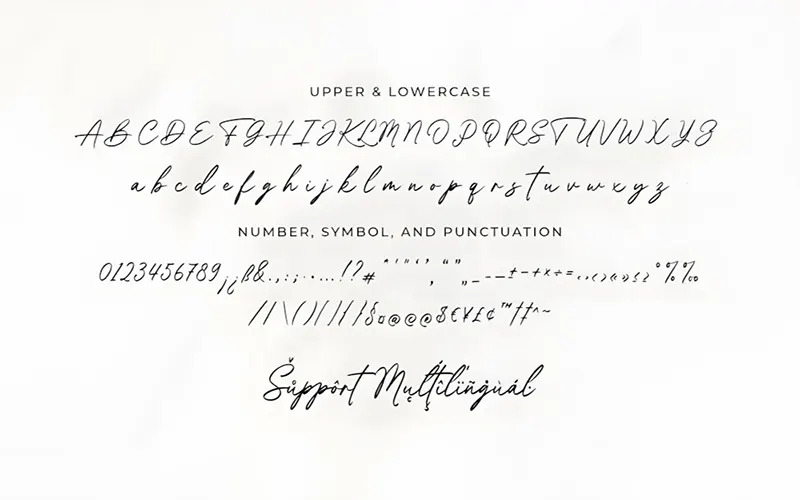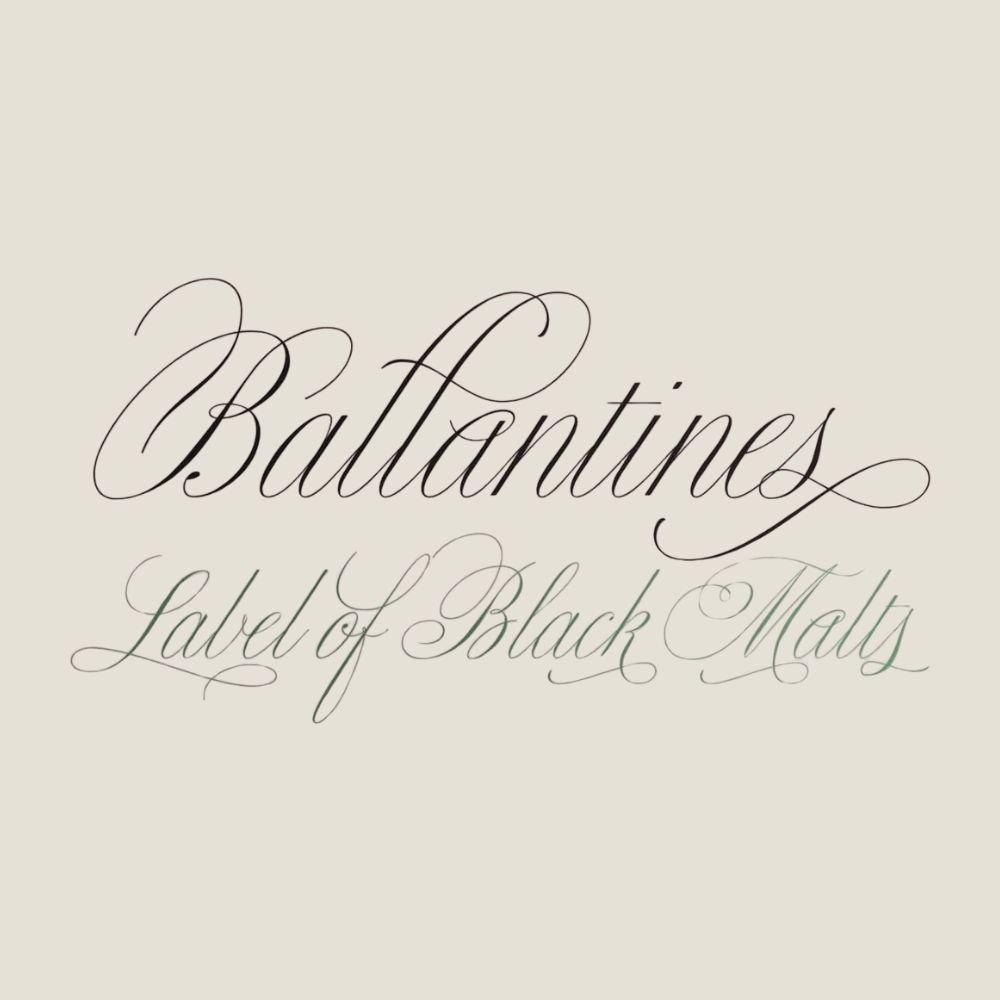
Font chữ kéo dài (thường được biết đến là các dòng phông chữ viết tay Calligraphy có nét uốn lượn đầu và đuôi chữ thướt tha) là lựa chọn hàng đầu của các designer khi cần tạo điểm nhấn mềm mại, bay bổng và đầy chất thơ cho bản thiết kế. Với đặc trưng là những đường nét móc đuôi kéo dài duyên dáng, bộ phông chữ này giúp các dòng tiêu đề thương hiệu, thiệp cưới sang trọng và bao bì mỹ phẩm toát lên vẻ đẹp quý phái, độc bản. Doozypack.vn chia sẻ link tải trọn bộ font chữ kéo dài đuôi đã được Việt hóa chỉn chu, giúp bạn thỏa sức sáng tạo mà không gặp bất kỳ lỗi hiển thị dấu thanh nào khi thiết kế in ấn.
Đặc điểm thẩm mỹ độc đáo của các bộ font chữ kéo dài
Không giống như những phông chữ tiêu chuẩn có ranh giới ký tự gò bó, các dòng font kéo dài mang đến một nhịp điệu Typography sống động, mô phỏng chân thực kỹ thuật vung bút điêu luyện của các nghệ nhân thư pháp.
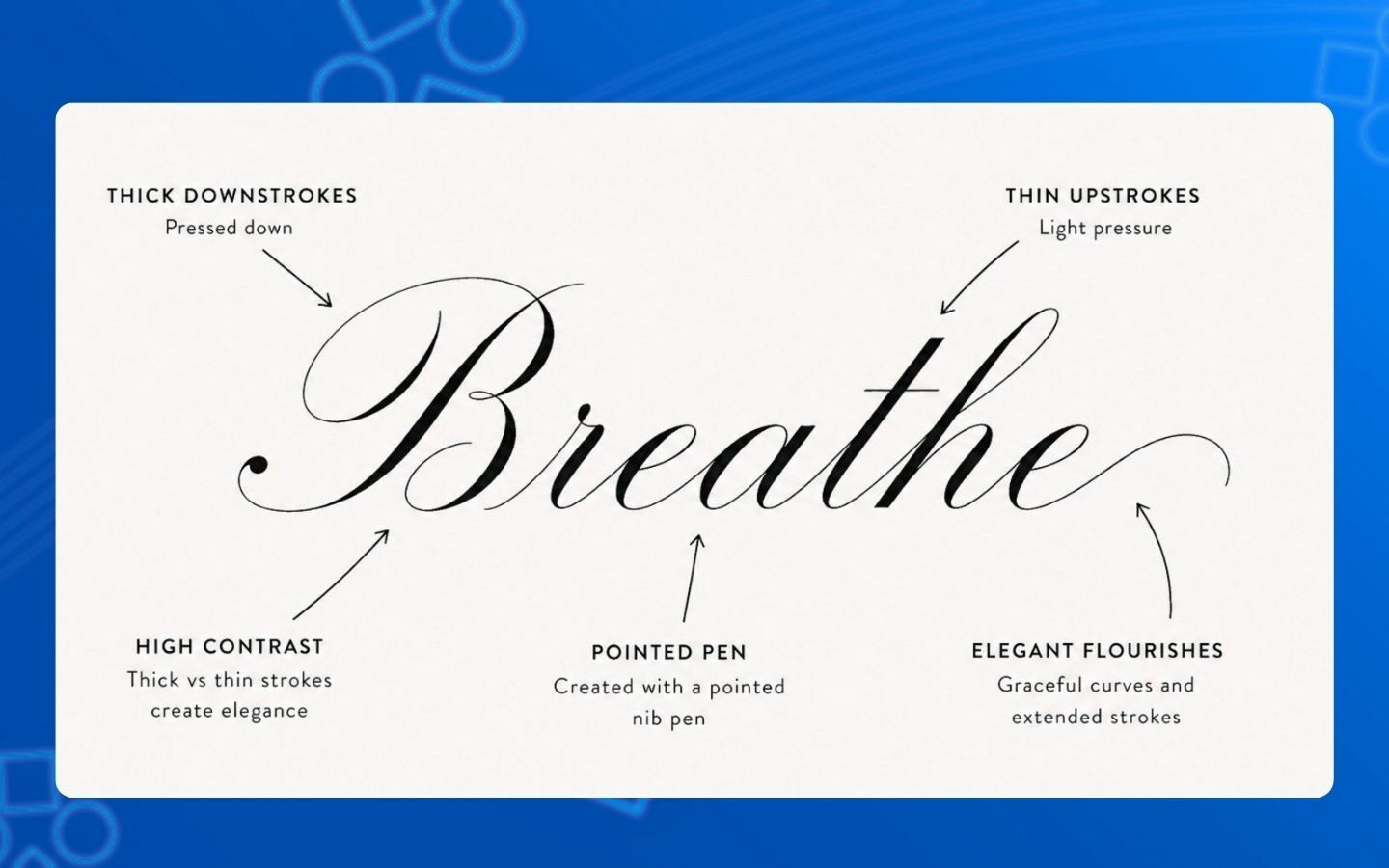
Đường nét uốn lượn thướt tha với các nét kéo dài đuôi nghệ thuật
Đặc trưng lớn nhất của Font chữ kéo dài là các ký tự mở đầu và kết thúc từ ngữ sở hữu những đường lượn sóng (swashes) vươn dài mềm mại. Nét chữ có thể uốn cong duyên dáng dưới chân chữ hoặc bay bổng vút lên trên, tạo thành một khung viền trang trí tự nhiên cho dòng chữ. Chi tiết đắt giá này giúp biến một cái tên thương hiệu thông thường thành một biểu tượng đồ họa tinh xảo, thu hút trọn vẹn ánh nhìn của khách hàng ngay từ cái nhìn đầu tiên trên bao bì.
Nhịp điệu chữ viết tay tự nhiên và giàu cảm xúc
Hầu hết các bộ font chữ viết tay kéo dài sở hữu sự tương phản rõ rệt giữa những nét đưa bút thanh mảnh như sợi tơ và các nét nhấn xuống đậm đà, chắc chắn. Đường chân chữ (baseline) có độ nhấp nhô nhẹ nhàng, gợi cảm giác như một bức thư tay cá nhân chan chứa tình cảm, cực kỳ phù hợp cho các thương hiệu theo đuổi phong cách lãng mạn, tinh tế và nữ tính.
Ưu điểm nổi bật của bản font kéo dài Việt hóa
Khi ứng dụng các phông chữ có nhiều nét uốn lượn vào thị trường trong nước, sự chỉn chu về dấu câu là yếu tố quyết định đến tính chuyên nghiệp của ấn phẩm:
- Khắc phục triệt để lỗi dấu tiếng Việt: Phiên bản Việt hóa chuẩn đã được đội ngũ thiết kế trau chuốt thủ công từng dấu câu. Các dấu sắc, huyền, hỏi, ngã, nặng được vẽ thanh mảnh, uốn lượn đồng điệu cùng thân chữ, không gây cảm giác chắp vá hay va chạm vào các đường nét kéo dài xung quanh.
- Bảo đảm tính đồng nhất thương hiệu: Việc sử dụng bản font kéo dài chuẩn giúp bạn tự tin dàn trang tiêu đề tiếng Việt mà không lo hiện tượng lỗi ô vuông hay nhảy về font hệ thống khô khan.
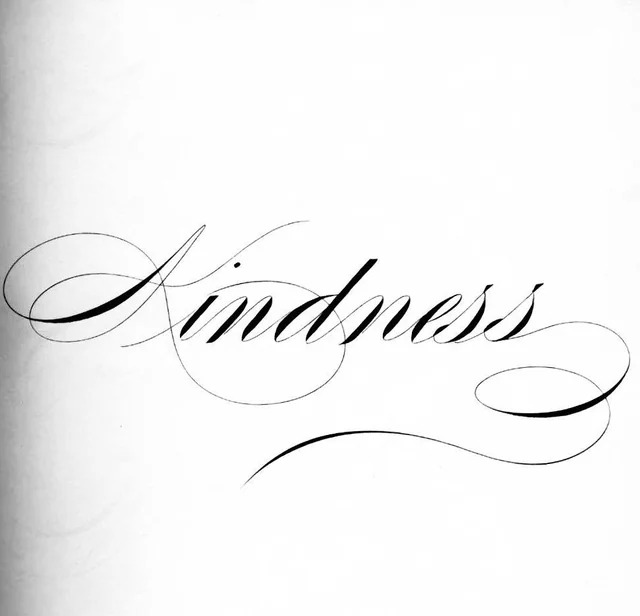
| Nhóm Font | Đặc điểm thị giác | Ứng dụng đề xuất tại Doozypack.vn |
| Modern Script kéo đuôi | Thanh lịch, lãng mạn, bay bổng | Tiêu đề hộp mỹ phẩm, nhãn nước hoa, thiệp mời cao cấp. |
| Signature kéo nét | Chữ ký phóng khoáng, cá tính | Thiệp cảm ơn (Thank-you card), túi giấy thời trang boutique. |
| Vintage Script uốn lượn | Cổ điển, nét đậm đà, sang trọng | Bao bì bánh ngọt, hộp trà thảo mộc, nhãn rượu vang. |
Ứng dụng thực tế của font chữ viết tay kéo dài trong sản xuất bao bì
Sự kiêu sa và duyên dáng của nhóm font này mang lại hiệu ứng thị giác đắt giá trên các dòng sản phẩm bao bì thực tế do Doozypack.vn sản xuất:
- Hộp giấy đựng Nước hoa & Mỹ phẩm Luxury: Tiêu đề thương hiệu in bằng nét chữ kéo dài đuôi kết hợp kỹ thuật ép kim nhũ vàng trên giấy Ivory cán màng mờ tạo nên vẻ đẹp sang trọng chuẩn quốc tế.
- Thiệp cưới & Thiệp cảm ơn cao cấp: Nét chữ viết tay uốn lượn là lựa chọn hoàn mỹ cho những lá thư tri ân đính kèm hộp quà, giúp gia tăng thiện cảm và sự gắn kết với khách hàng.
- Túi giấy thời trang cao cấp: Tiêu đề thương hiệu in bằng font chữ kéo dài màu đen tối giản trên nền túi giấy trắng giúp cửa hàng toát lên gu thẩm mỹ tinh tế và đẳng cấp.
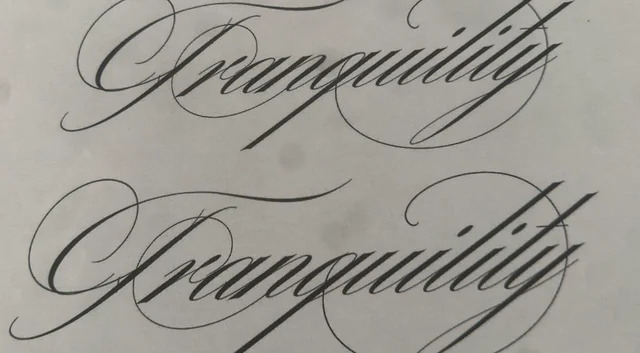
03 Lưu ý kỹ thuật khi in ấn với phông chữ kéo dài đuôi thanh mảnh
Việc sản xuất bao bì thực tế sử dụng các phông chữ có đường nét uốn lượn vươn dài đòi hỏi sự am hiểu kỹ thuật chuyên sâu tại xưởng in Doozypack.vn:
- Lưu ý khoảng cách an toàn (Safe Zone): Do các nét đuôi chữ thường vươn dài ra hai bên, designer cần chừa khoảng cách an toàn cách mép cấn bế bao bì tối thiểu 5mm để tránh bị lưỡi dao cắt lẹm vào nét uốn lượn của chữ.
- Kiểm soát độ dày nét Hairline khi ép kim: Các nét vuốt đuôi nối chữ của font chữ này khá thanh mảnh. Khi gia công ép kim vàng (Hot Stamping), designer nên đảm bảo nét chữ có độ dày tối thiểu 0.15mm để nhũ bám dính sắc nét, không bị đứt đoạn.